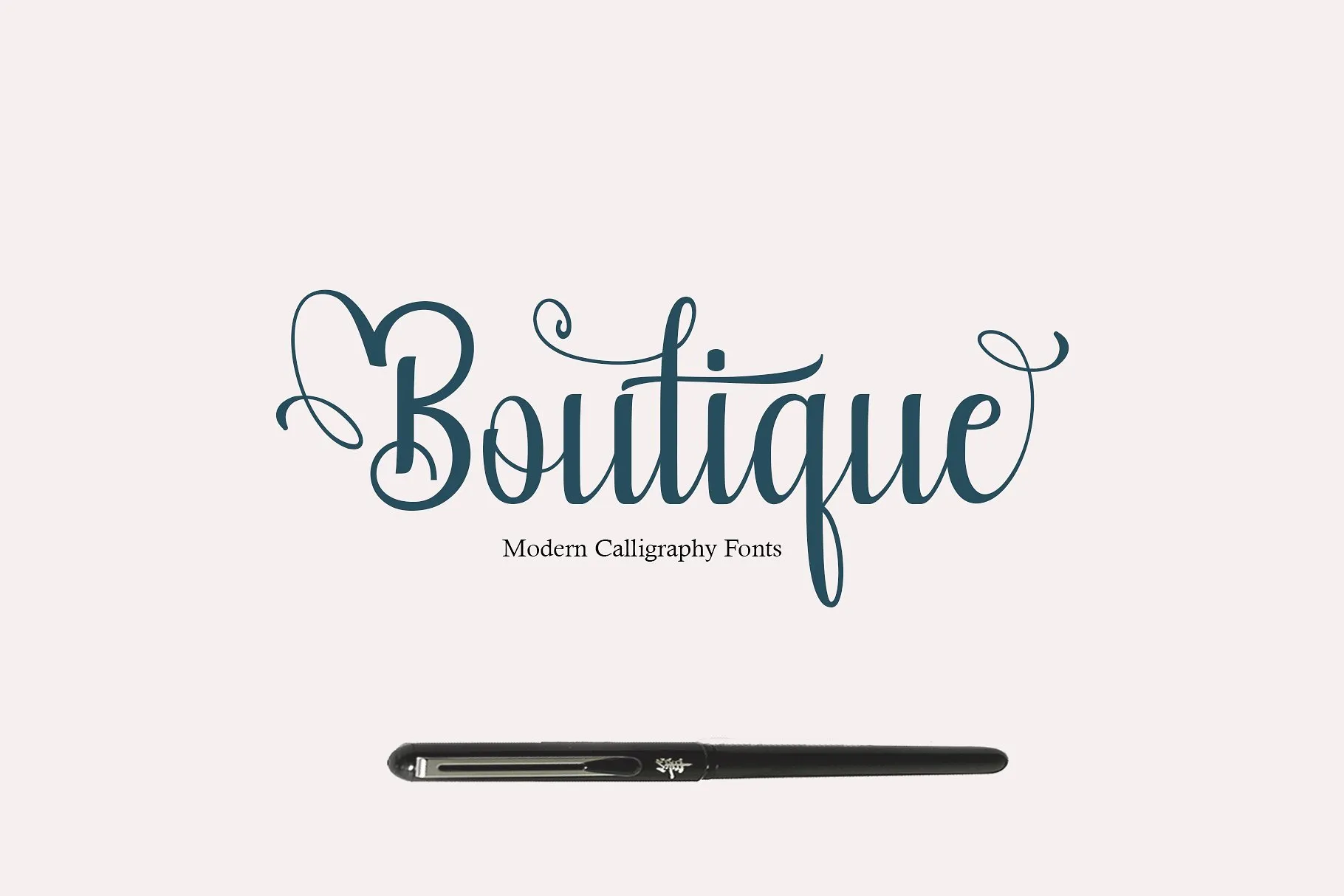
Boutique Calligraphy Font – Download Grátis
A Boutique Calligraphy Font é uma fonte moderna criada especialmente para aqueles que buscam um toque elegante nas suas criações. Introduzida por Deniz86, essa fonte tem características puramente manuscritas e carrega a essência natural da escrita. Perfeita tanto para convites quanto para assinaturas, blogs, perfis sociais, cartões de empresa ou marcas de produtos, ela oferece um resultado que transmite autenticidade e beleza sem igual. Se você está procurando por uma fonte que seja mais do que apenas texto, mas também parte da sua identidade visual, a Boutique Calligraphy Font é a escolha certa. Com seu estilo elegante e natural, essa font pode transformar suas mensagens em algo único e envolvente, capaz de destacar seus projetos entre os demais. Deniz86 não apenas criou esse trabalho, ele também compartilhou sua arte com o público, tornando-a disponível para que muitas outras pessoas possam aproveitar e inspirar-se com suas obras.